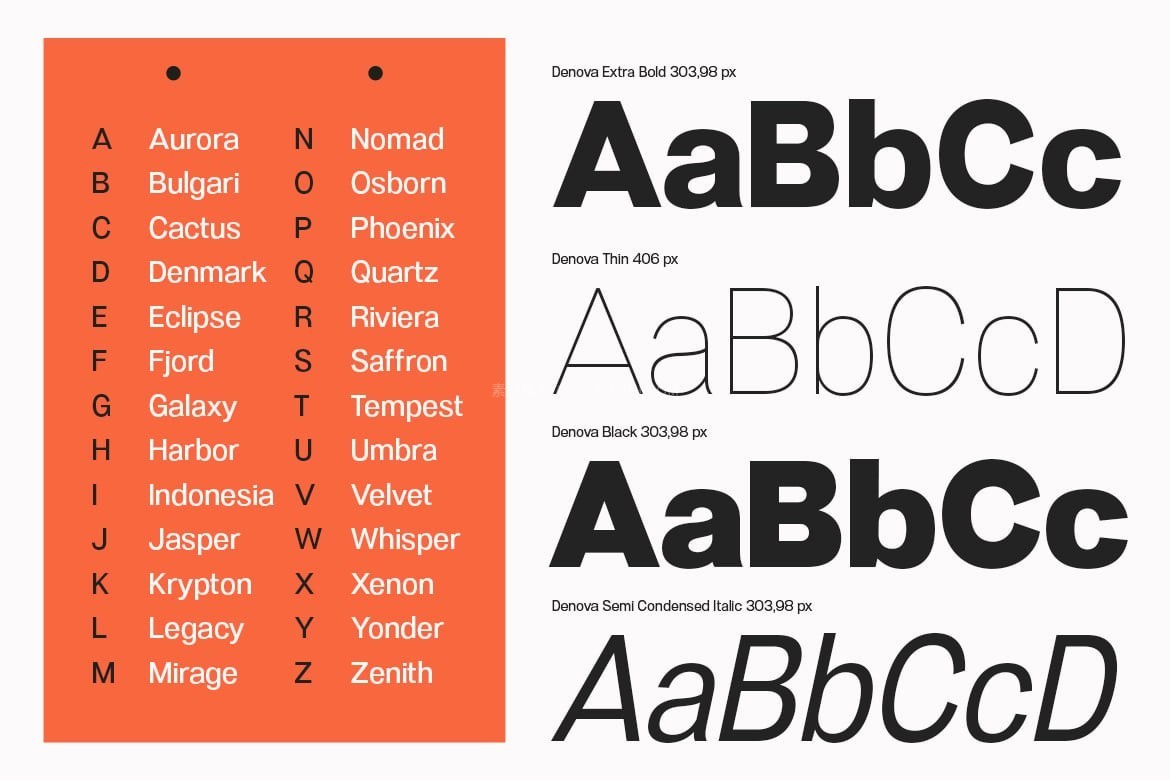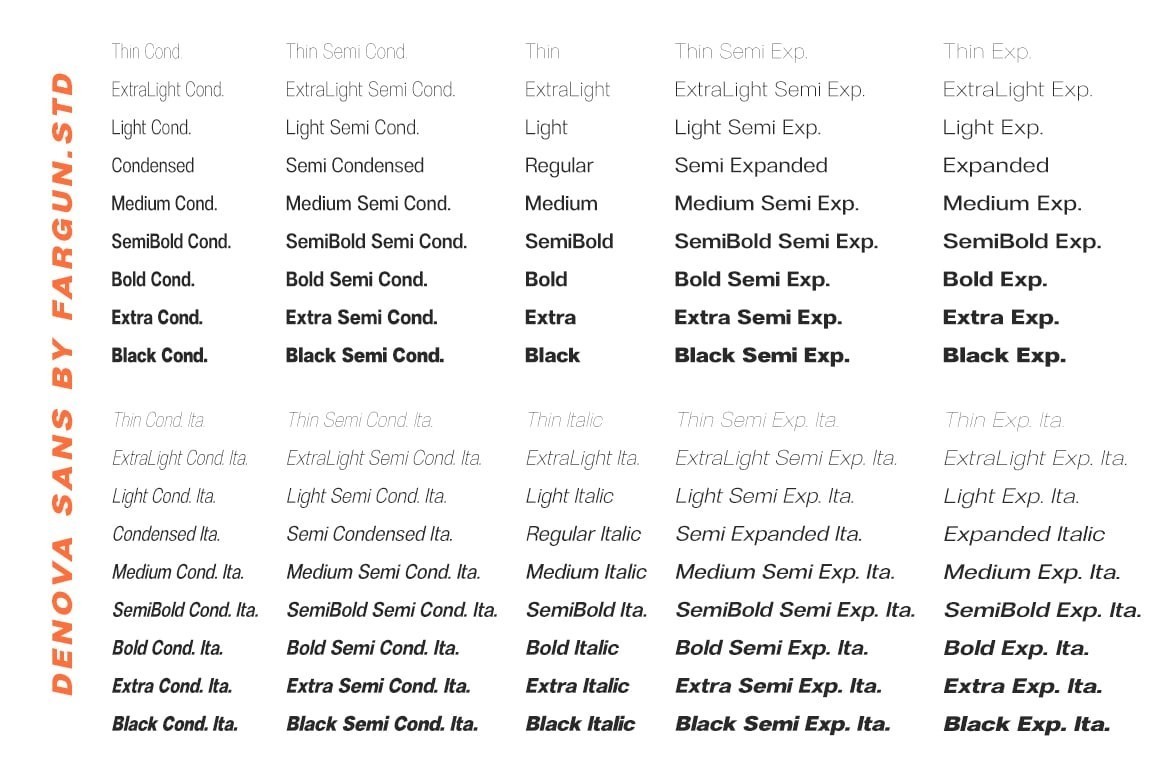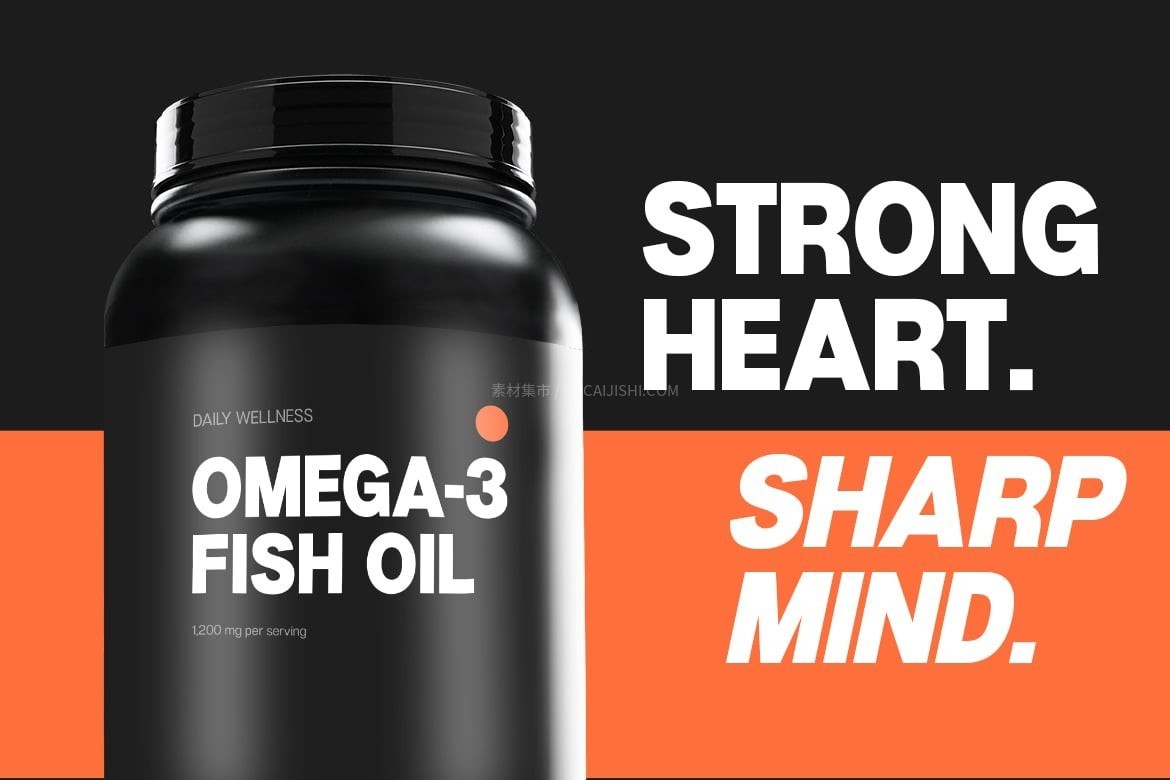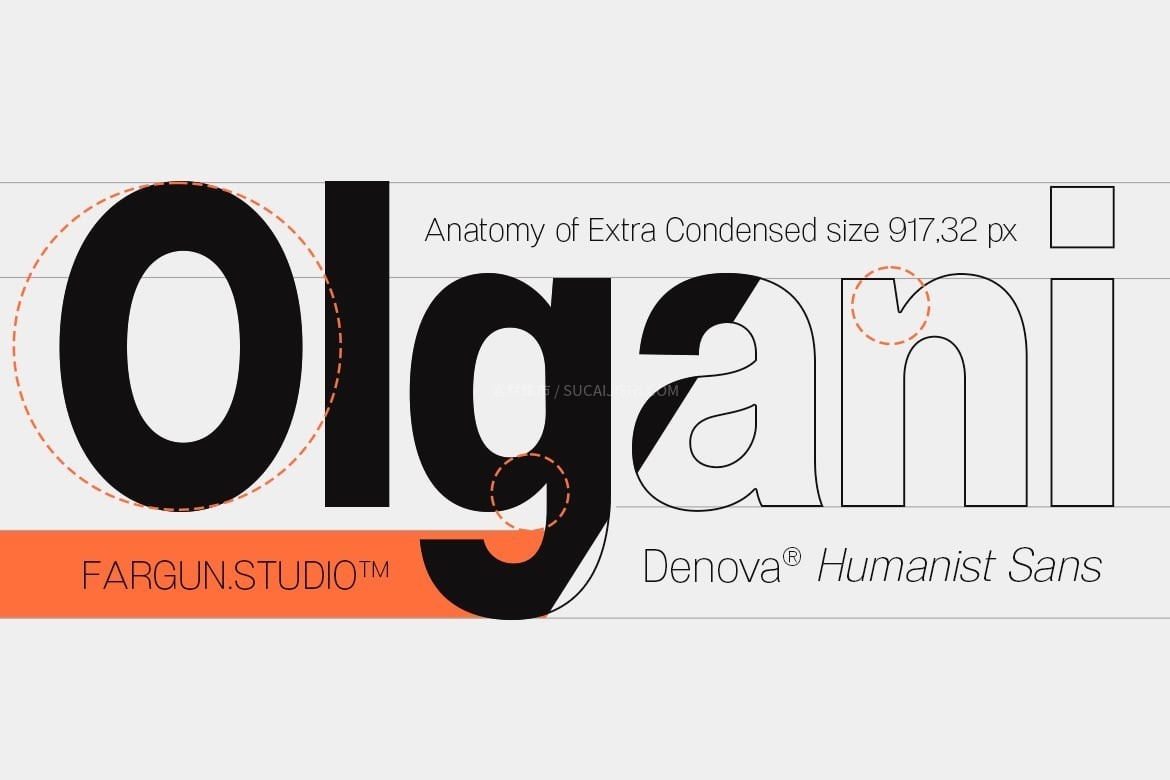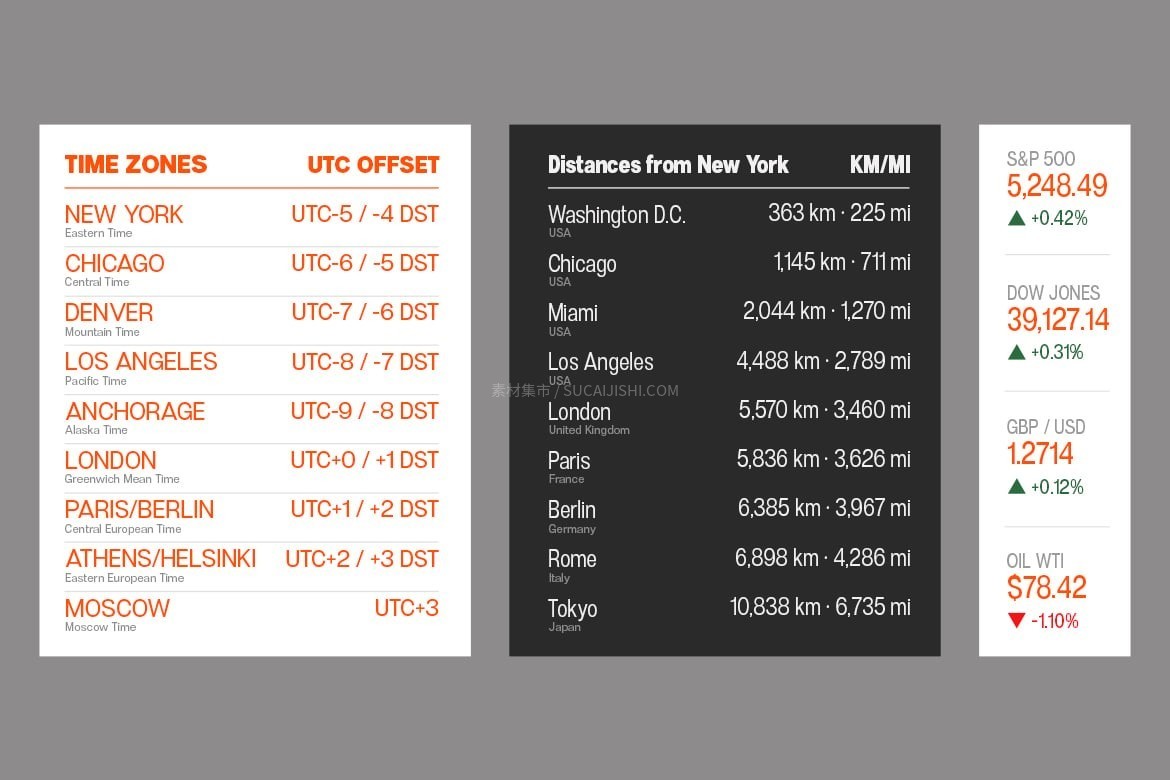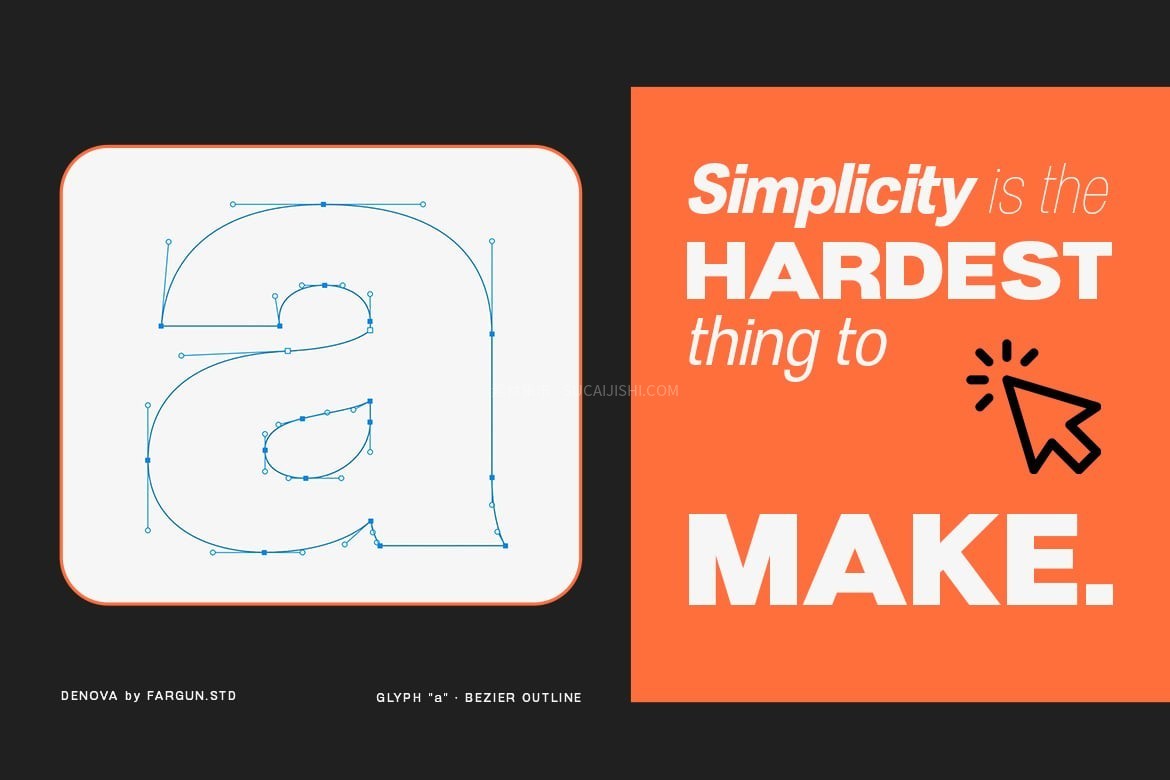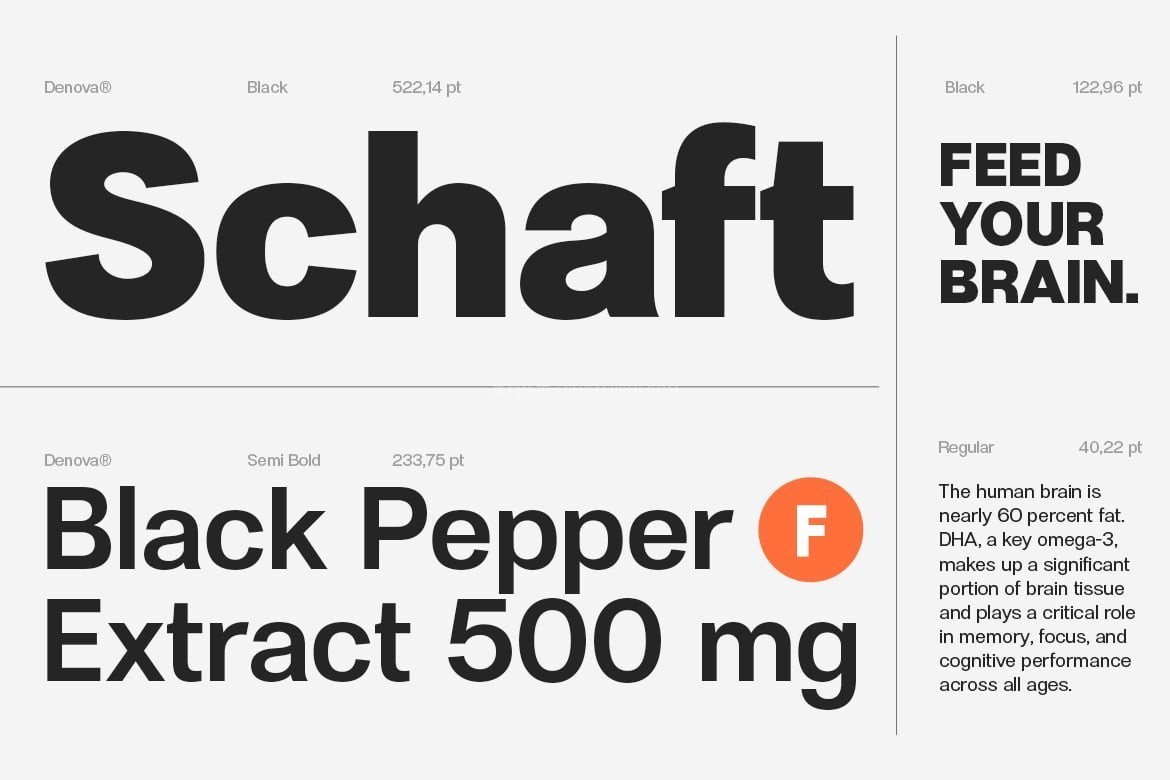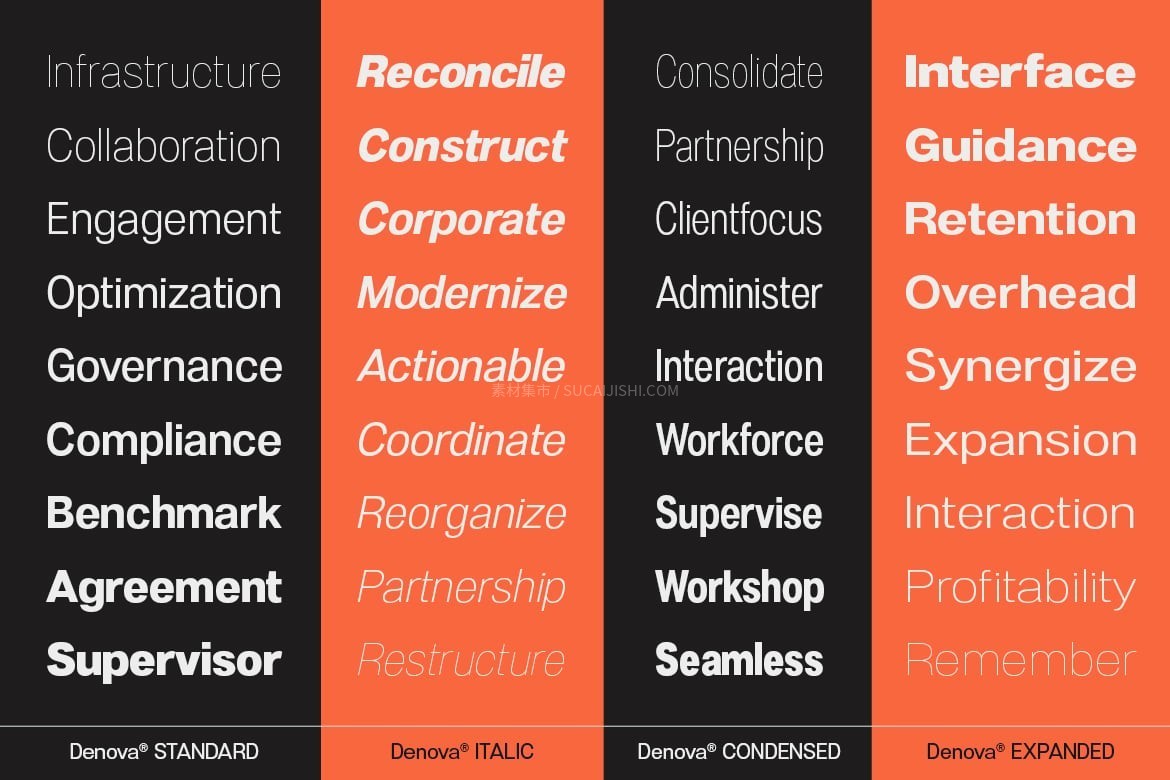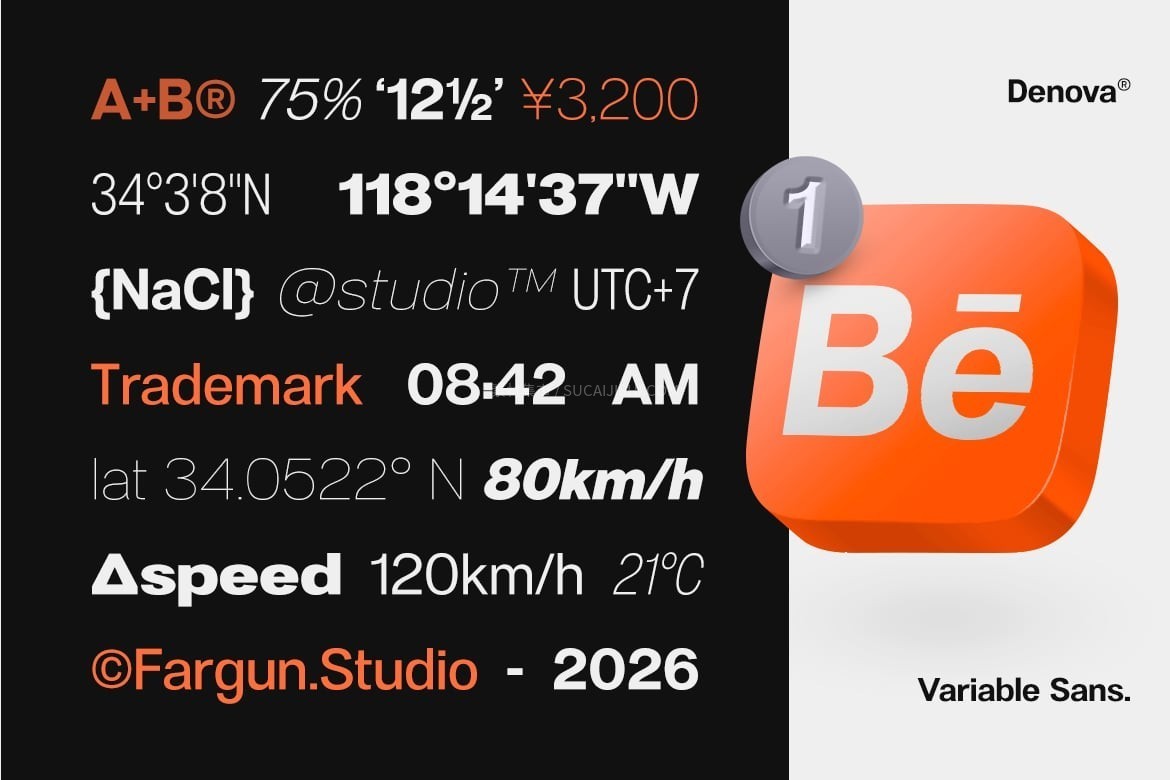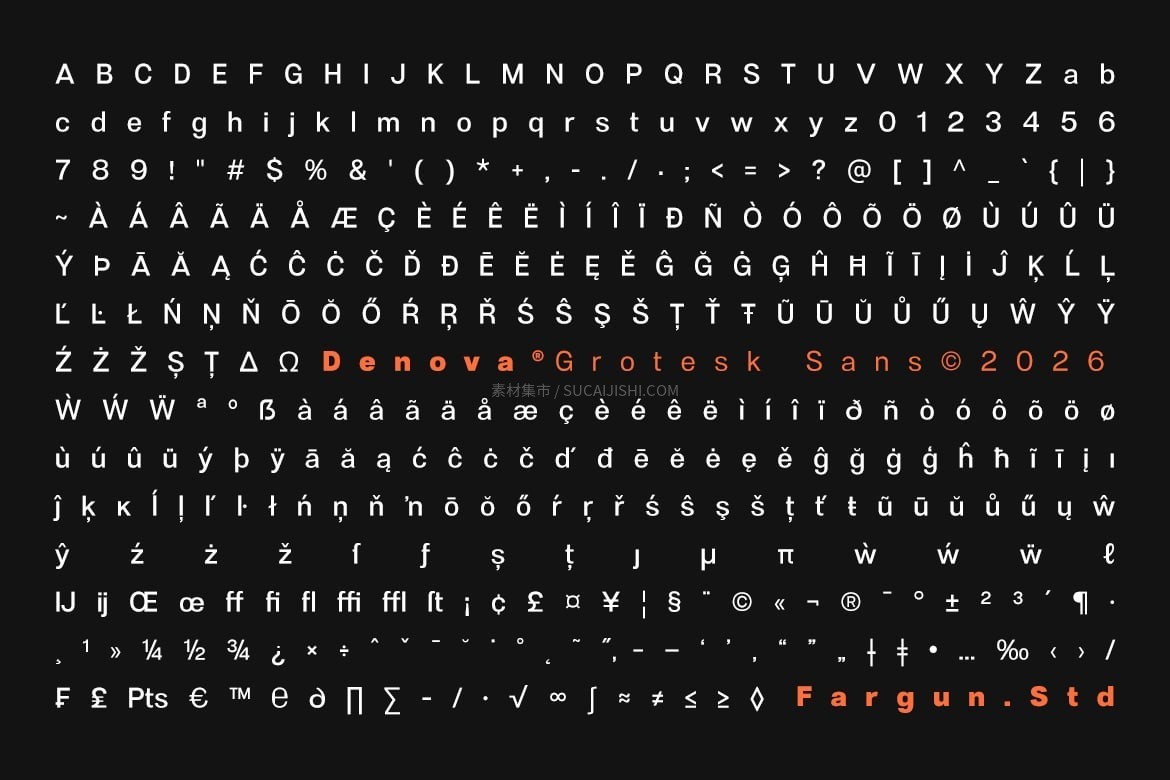
Denova Sans 可变无衬线字体(90种样式)
这款 Denova Sans 是一款专为现代排版量身打造的可变无衬线字体!它巧妙地将清晰干练的线条与柔和的人文主义曲线结合在一起,看起来既专业高级又充满亲和力。不管是用于屏幕 UI 显示还是画册印刷,它的阅读体验都超级棒。作为一款全能的排版神器,它包含了高达 90 种样式,提供丰富的字重和字宽选择,并自带正体和斜体。